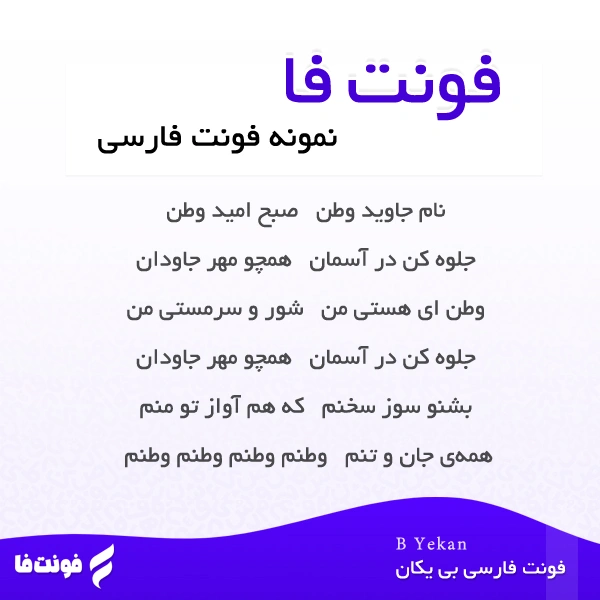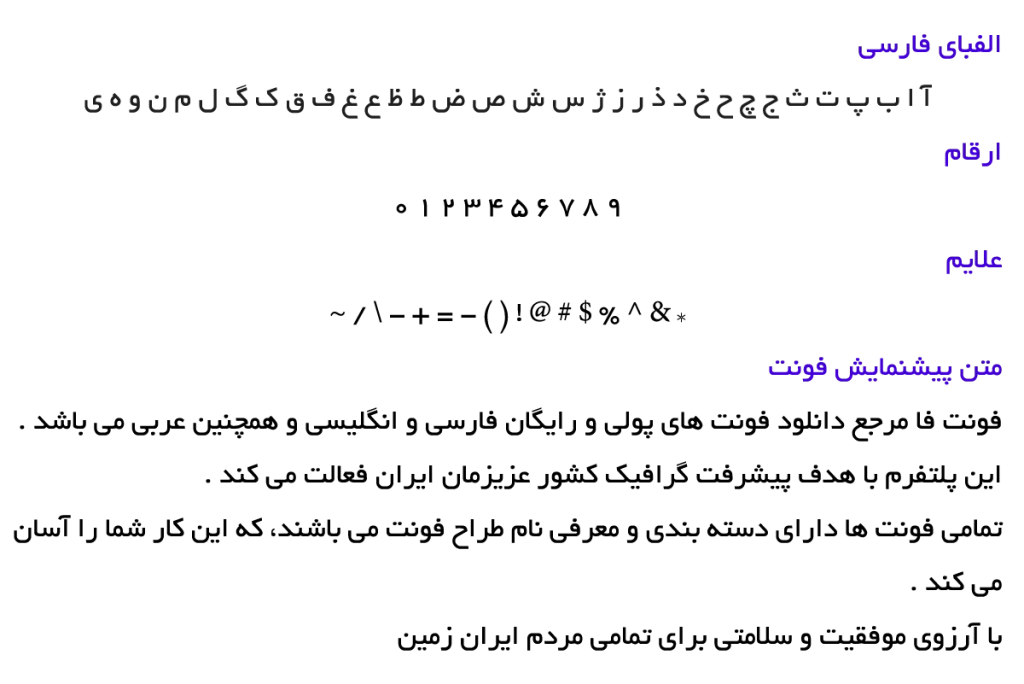
پیشنمایش فونت بی یکان
فونت فارسی بی یکان - B Yekan
توضیحات و معرفی فونت بی یکان
فونت فارسی بی یکان ( B Yekan ) از مجموعه فونت های آزاد می باشد، همچنین نوع فونت متن می باشد.
فونت فوق العاده زیبای معرفی شده توسط برنا رایانه در سال 1379 طراحی و ساخته شده است.
بی یکان فونتی خوشگل است که نسخه قدیمی فونت یکان پلاس و فونت ایران یکان دارد.
این تایپ فیس یکی از پردانلود ترین و محبوب ترین فونت های قدیمی ایرانی بود.
همچنین فونت B Yekan در یک وزن معمولی است.
در لیست زیر می توانید وزن این فونت فوق العاده زیبا را ببینید.
• B Yekan Regular
در تصویر زیر پیش نمایش این تایپ فیس را مشاهده می‌کنید.
پیشنمایش فونت بی یکان
در تصویر زیر میتوانید تفاوت کلی این تایپ فیس را با فونت یکان پلاس مشاهده کنید…
مقایسه بی یکان و یکان پلاس